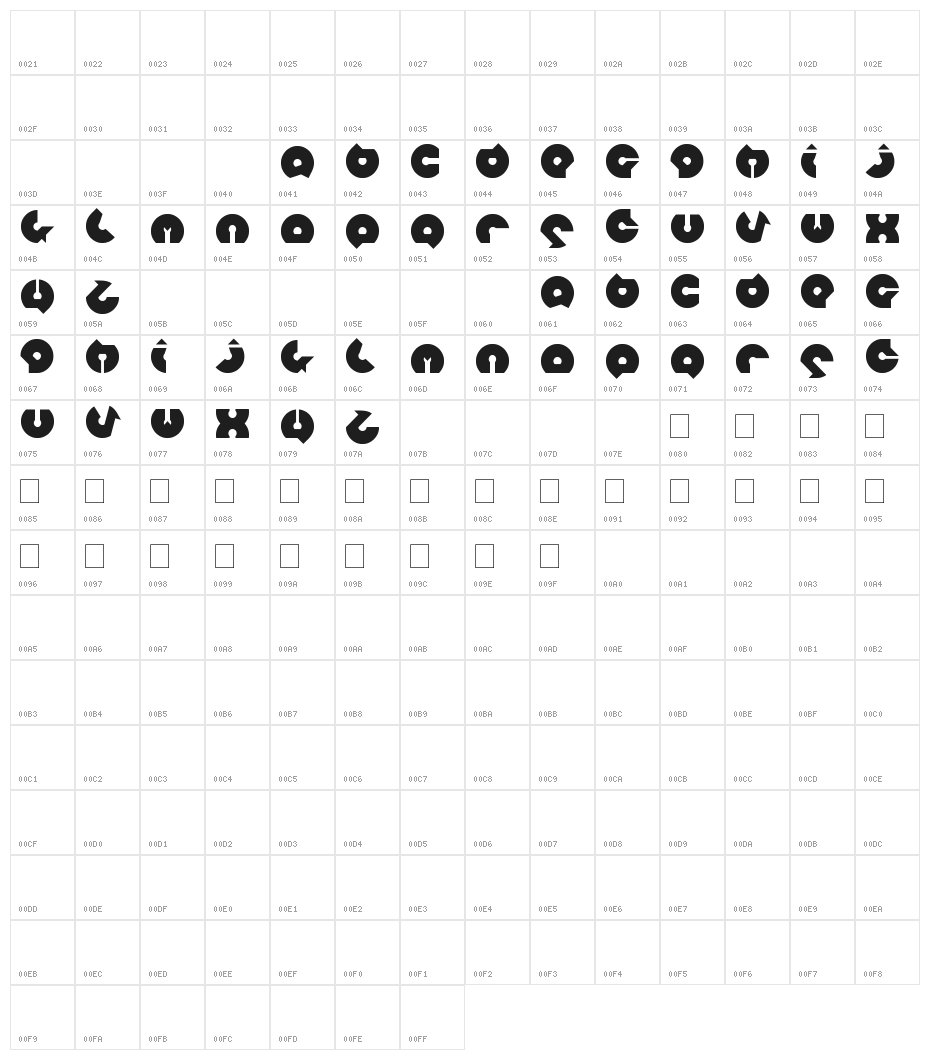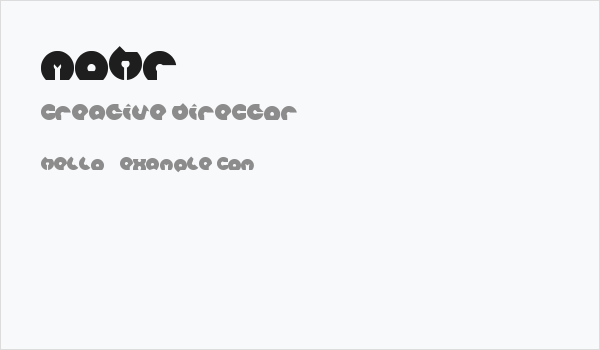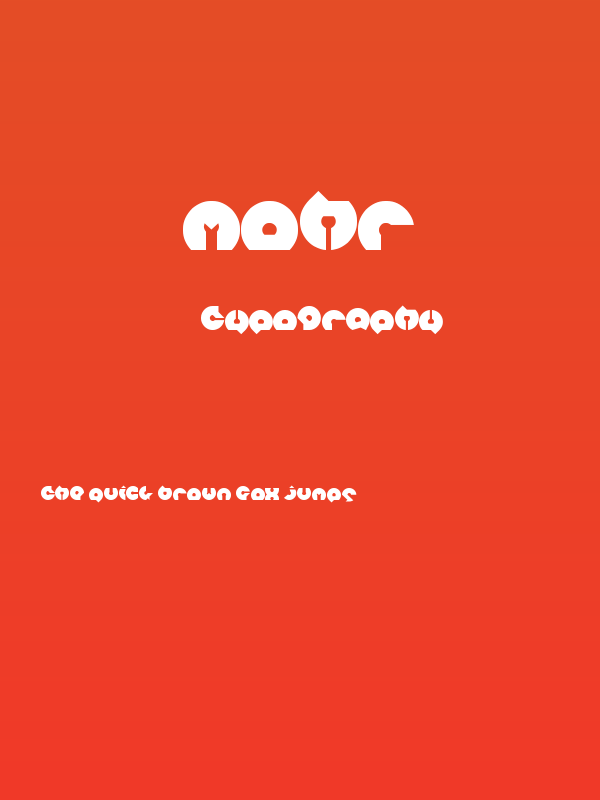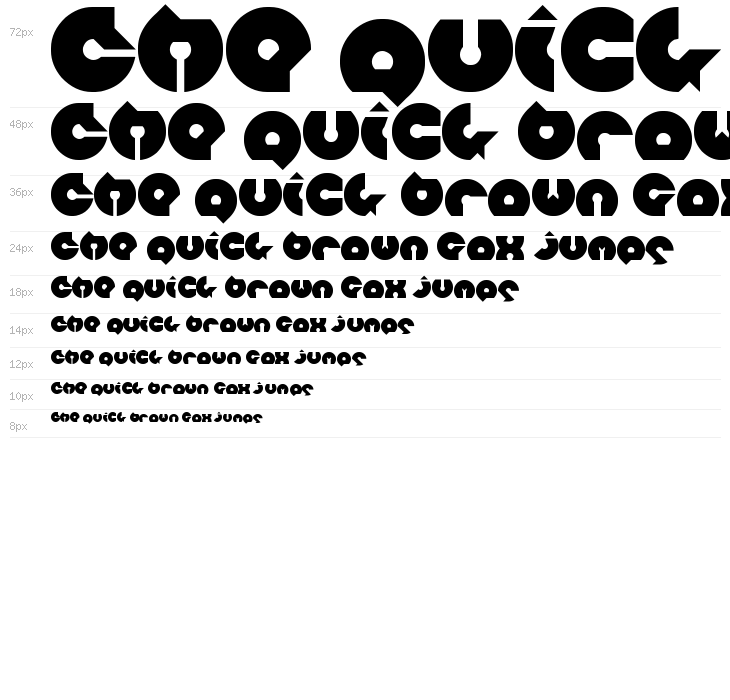
mohr Font
| Stile generale | Futuristic, Modern |
| Progetti proposti | Ideal for branding, posters, album covers, and any project needing a modern, standout typeface. |